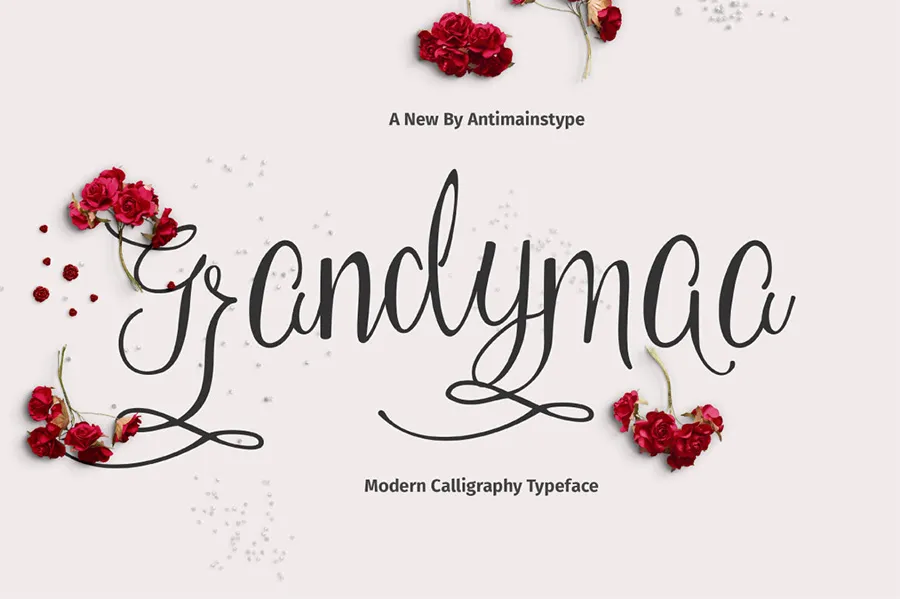
Grandymaa Script é uma nova face de tipografia cursiva lançada pelo designer Encik Ajir. Este tipo de letra tem um toque casual e elegante, com os caracteres dançando ao longo do alinhamento horizontal (baseline). É perfeito para vários usos, desde logotipos e cartões de convite de casamento até selos, rótulos, carteiras, sinálgas, anúncios e até mesmo em letras de notícias. Grandymaa Script oferece um equilíbrio entre elegância e naturalidade que torna a fonte uma escolha ótima para designers buscando adicionar um toque único a seus projetos. Com sua capacidade versátil, Grandymaa Script é certamente uma opção ideal para estilos de design criativos e modernos.